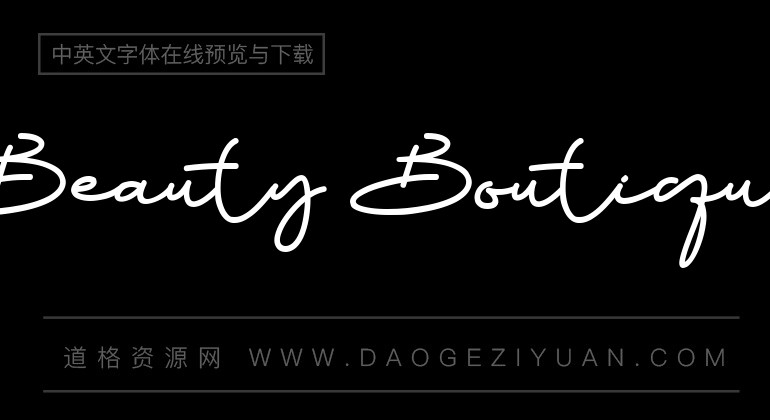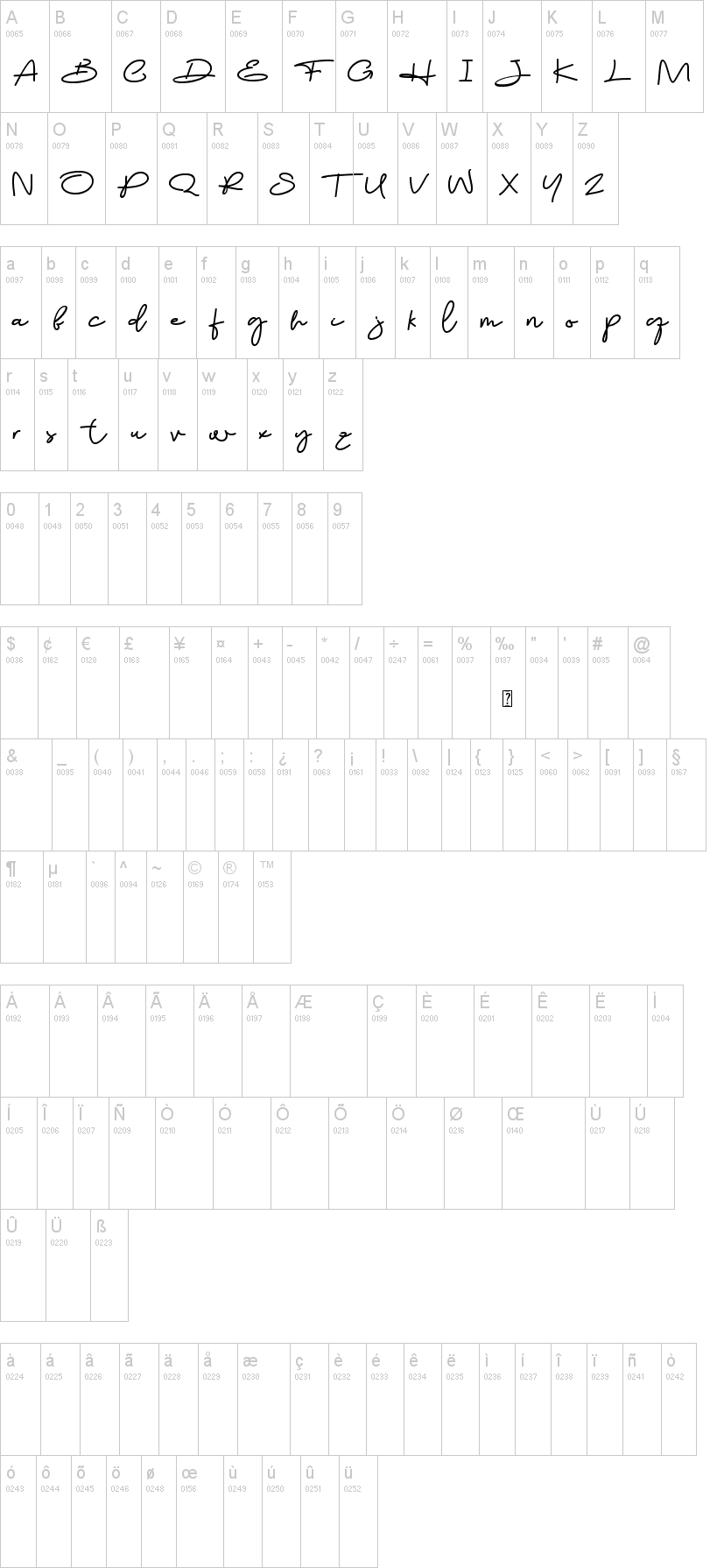
很抱歉,作为一个语言模型,我没有能力直接展示字体的外观。但是我可以告诉您一些关于 Beauty Boutique 字体的信息。 Beauty Boutique 是一种美观的手写字体,字母有着流畅的曲线和优雅的笔画。它通常被用于女性相关的品牌或设计,因为它具有优雅、精致、柔和的特点。字母之间的间距很小,整个字体呈现出一种温暖、亲近的感觉,适合用于标题、标志、广告等。 Beauty Boutique 字体可以在许多网站和应用程序上下载,也可以通过付费或免费方式获得。如果您需要一种适合女性品牌的字体,那么 Beauty Boutique 可能是一个不错的选择。内容介绍
Beauty Boutique是一款非常不错的手写艺术字体,具有很好的视觉感,适合于文化类的宣传设计、商业类品牌的广告和产品包装设计以及个性化文字排版等较多场景。